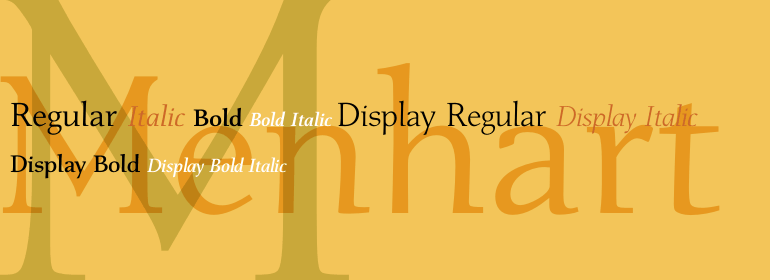
Menhart™
Menhart™,这款字体结构工整、笔画清晰,兼顾美观与易读性,适用于标题、正文、海报、包装、LOGO 等多种场景。字形优雅稳定,风格百搭耐看,适配日常排版与创意设计,让文字呈现更舒适、更具质感。Menhart™一笔一画,皆是细节,以均衡的比例、流畅的线条打造舒适视觉体验,字形端正大气,风格简约现代。无论是商业设计、品牌宣传还是日常排版,都能轻松驾驭,让文字更有格调与力量。Menhart™字体下载。
字体品牌: Monotype 设计师:Menhart,Oldrich 字体分类:衬线体 字体属性:外文 字符集:Unicode 发布时间: 2018